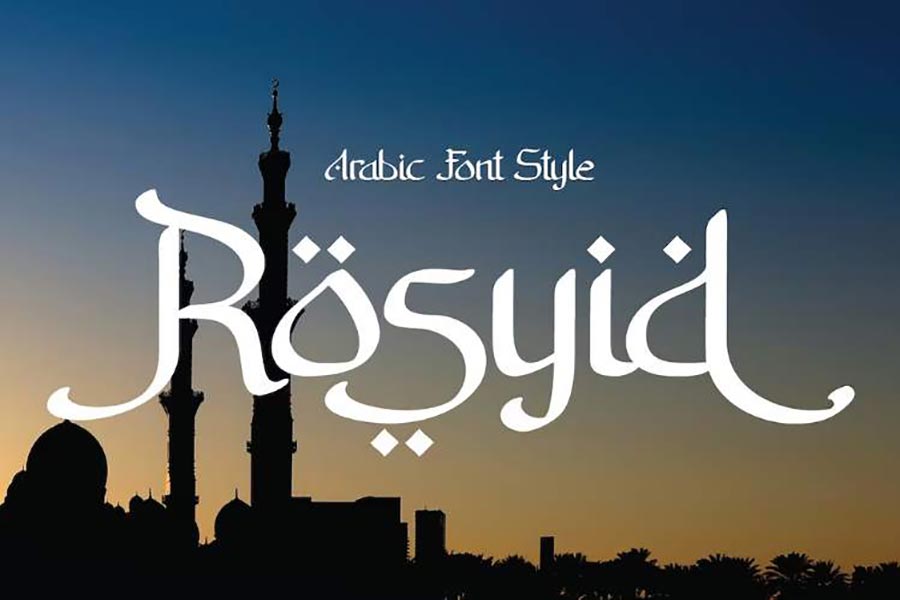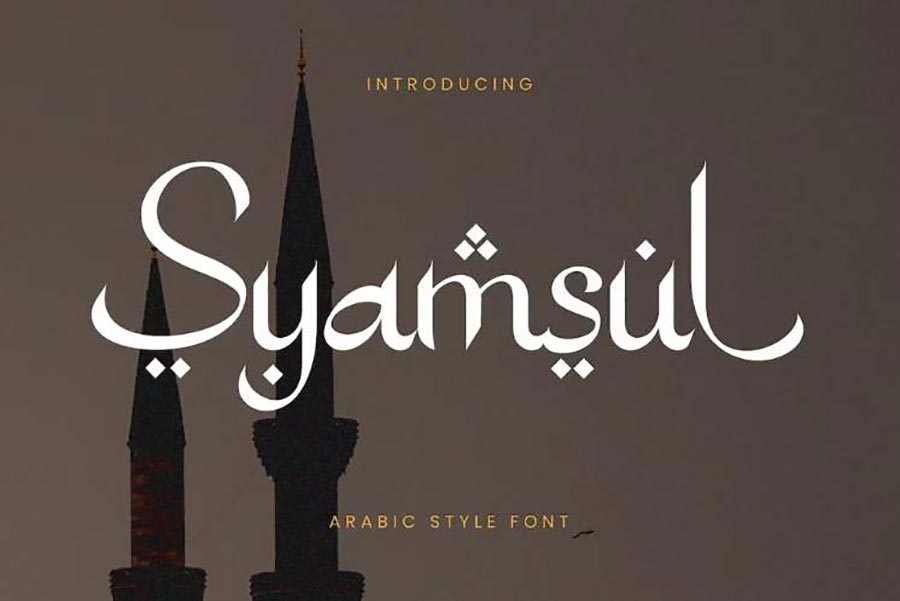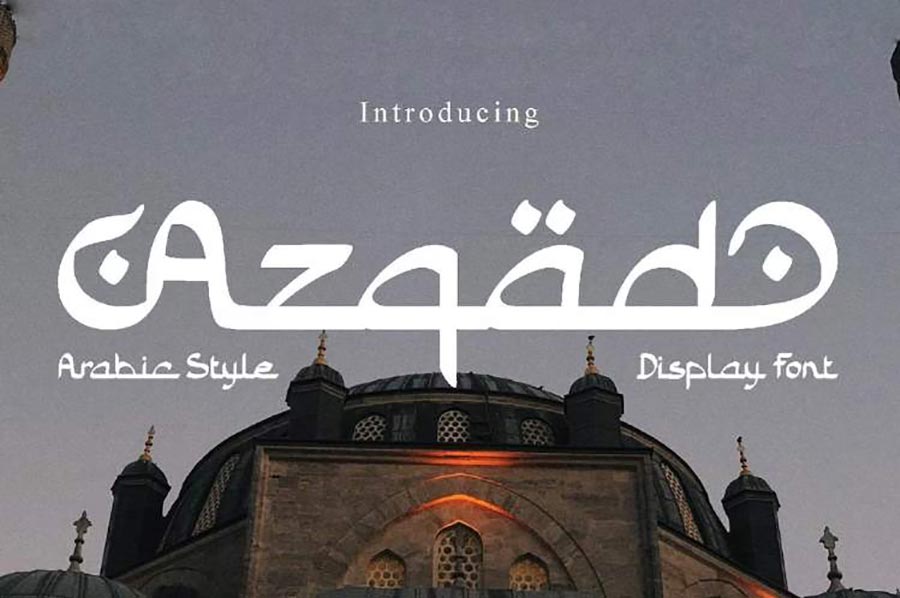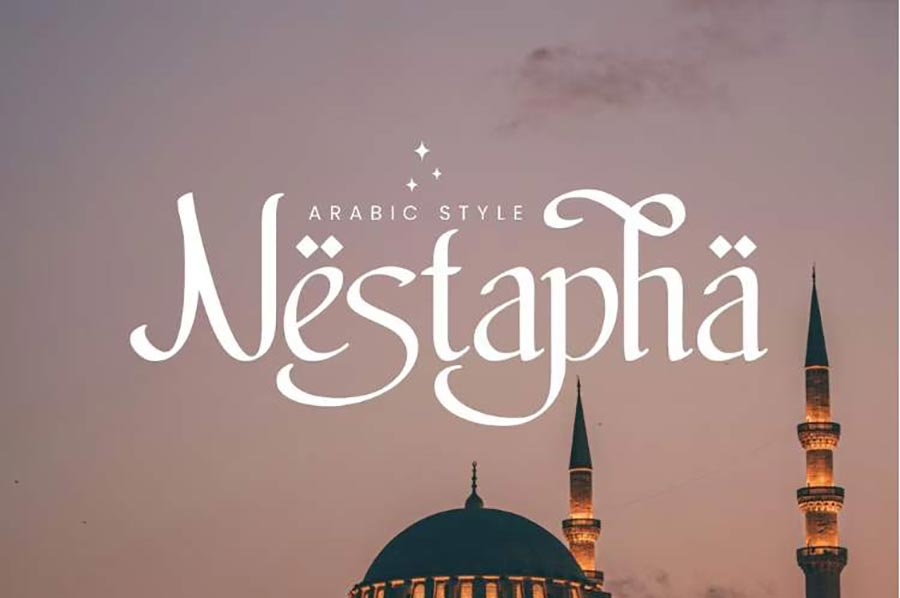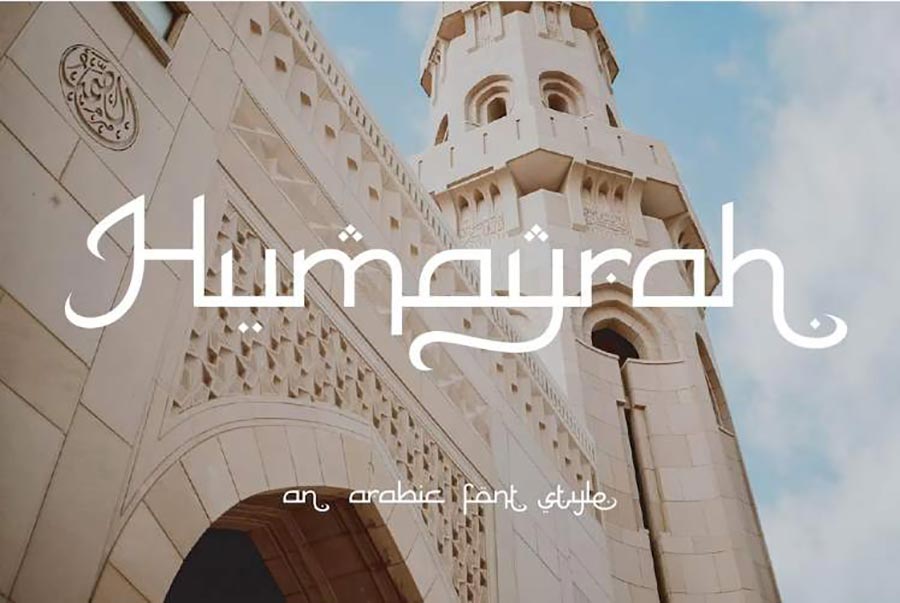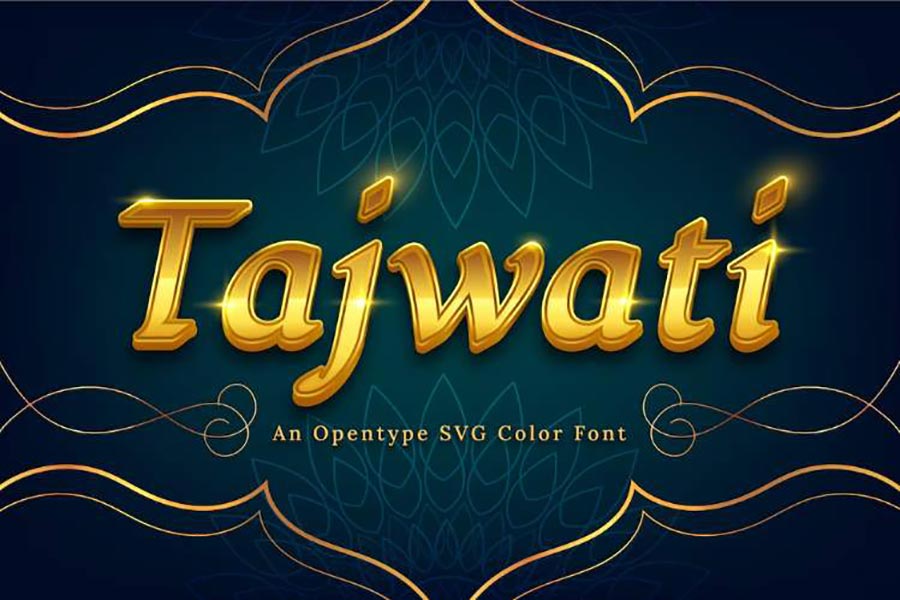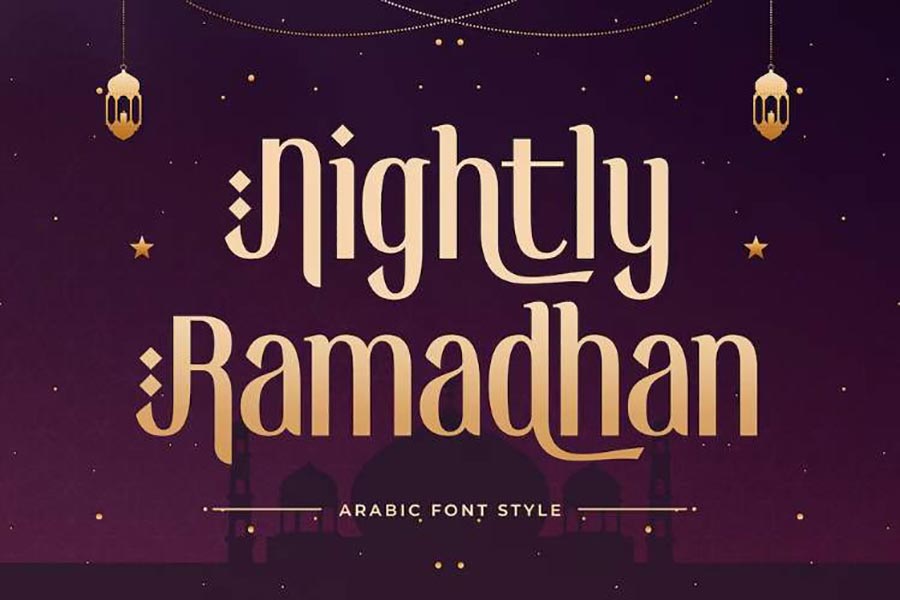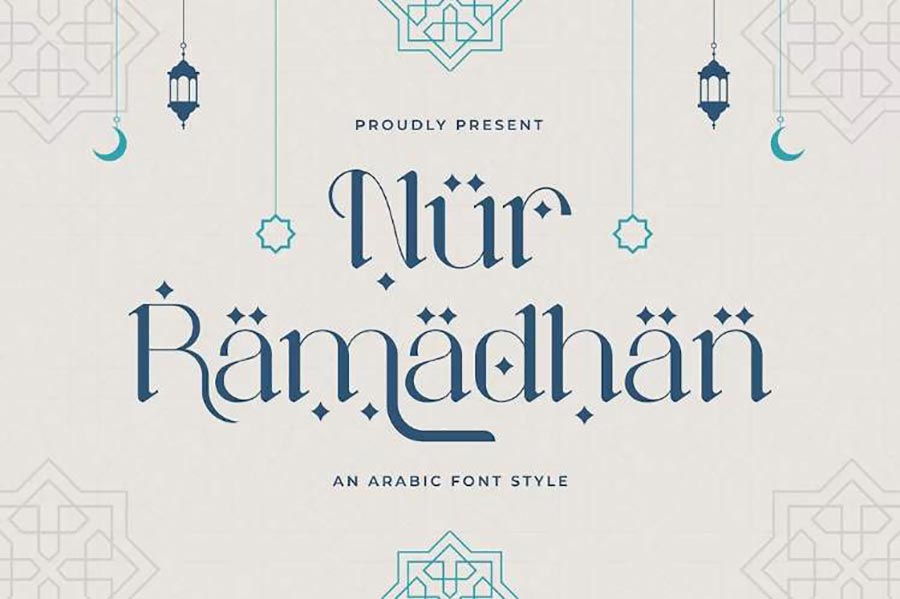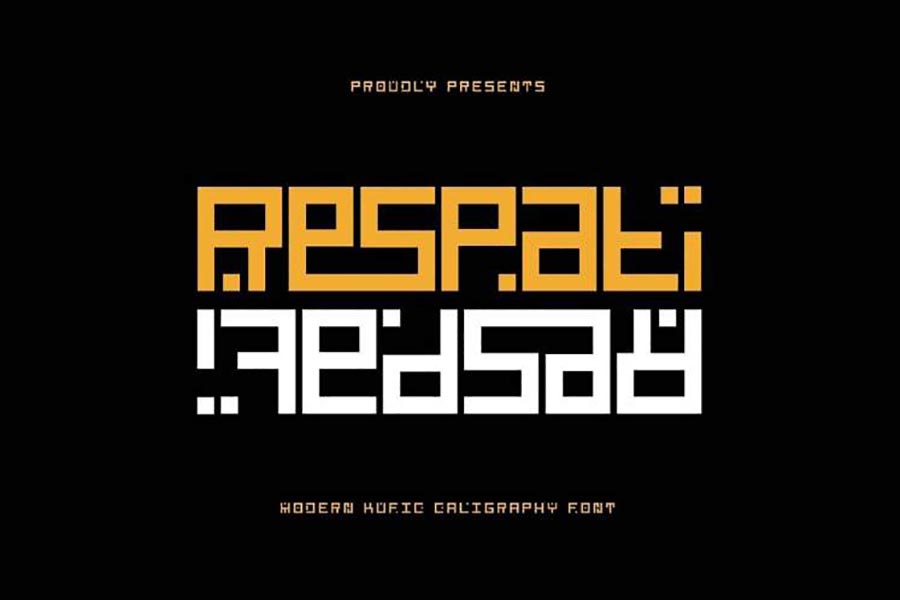
Trong thiết kế đồ họa, lựa chọn font chữ phù hợp là yếu tố then chốt giúp tạo nên sự ấn tượng và tính thẩm mỹ cho các sản phẩm. Đặc biệt, đối với những designer yêu thích sự độc đáo, mới lạ, font chữ Arabic (chữ Ả Rập) chính là một lựa chọn tuyệt vời. Bộ Fonts Arabic miễn phí từ Sadesign.vn sẽ là công cụ lý tưởng giúp bạn tạo ra các thiết kế mang đậm phong cách phương Đông, từ các sản phẩm quảng cáo đến thiệp mời, banner, hay logo. Trong bài viết này, chúng tôi sẽ hướng dẫn bạn cách tải và ứng dụng bộ Fonts Arabic tuyệt đẹp này để nâng cao chất lượng thiết kế của mình.
Fonts Arabic Là Gì?
Fonts Arabic là các font chữ mang đậm ảnh hưởng của chữ Ả Rập, với những đường nét uốn lượn, mềm mại và phong cách độc đáo. Loại font này không chỉ sử dụng trong các thiết kế liên quan đến văn hóa Ả Rập mà còn rất phổ biến trong việc tạo ra những sản phẩm thiết kế mang đậm tính nghệ thuật và truyền thống phương Đông. Fonts Arabic thường được dùng trong các lĩnh vực như quảng cáo, thiết kế sách, bao bì, poster, và đặc biệt là trong các dự án thiết kế liên quan đến sự kiện, lễ hội mang hơi hướng văn hóa Á Đông. Bộ Fonts Arabic miễn phí tại Sadesign.vn sẽ mang đến cho bạn nhiều lựa chọn phong phú, giúp bạn tạo ra những tác phẩm thiết kế ấn tượng và đặc sắc.
Ứng Dụng Bộ Fonts Arabic Trong Thiết Kế:
Bộ Fonts Arabic từ Sadesign.vn có thể được sử dụng cho nhiều loại thiết kế khác nhau. Dưới đây là một số ứng dụng phổ biến như sau:
1. Thiết Kế Logo: Fonts Arabic với những đường nét uốn lượn rất phù hợp để tạo ra những logo độc đáo, mang đậm dấu ấn cá nhân, thể hiện sự sáng tạo trong công việc thiết kế.
2. Thiết Kế Poster và Banner: Fonts Arabic là lựa chọn tuyệt vời để thiết kế các poster, banner cho các sự kiện, lễ hội, hay chiến dịch quảng cáo, giúp truyền tải thông điệp một cách mạnh mẽ.
3. Thiết Kế Bao Bì: Sử dụng font chữ Arabic trong thiết kế bao bì sẽ tạo nên sự sang trọng và mới lạ, thu hút sự chú ý của khách hàng.
4. Thiết Kế Thiệp Mời: Nếu bạn đang tổ chức các sự kiện mang đậm văn hóa phương Đông, Fonts Arabic sẽ giúp bạn thiết kế thiệp mời và các tài liệu liên quan với vẻ đẹp tinh tế và sang trọng.
5. Nội Dung Mạng Xã Hội: Để tạo ra các bài đăng ấn tượng trên Instagram, Facebook hay các nền tảng mạng xã hội khác, bạn có thể dùng Fonts Arabic để tạo ra những câu quote đầy cảm hứng, dễ dàng thu hút sự chú ý.
Bộ Fonts Arabic miễn phí từ Sadesign.vn là một tài nguyên quý giá cho các designer đang tìm kiếm những font chữ độc đáo, sang trọng và dễ dàng ứng dụng vào các dự án thiết kế. Với những kiểu chữ mang đậm ảnh hưởng văn hóa phương Đông, bộ font này sẽ giúp bạn tạo ra các sản phẩm thiết kế đầy ấn tượng, từ logo, thiệp mời, poster, đến bao bì sản phẩm. Hãy nhanh tay tải bộ Fonts Arabic miễn phí từ Sadesign.vn để nâng cao chất lượng thiết kế của bạn ngay hôm nay.